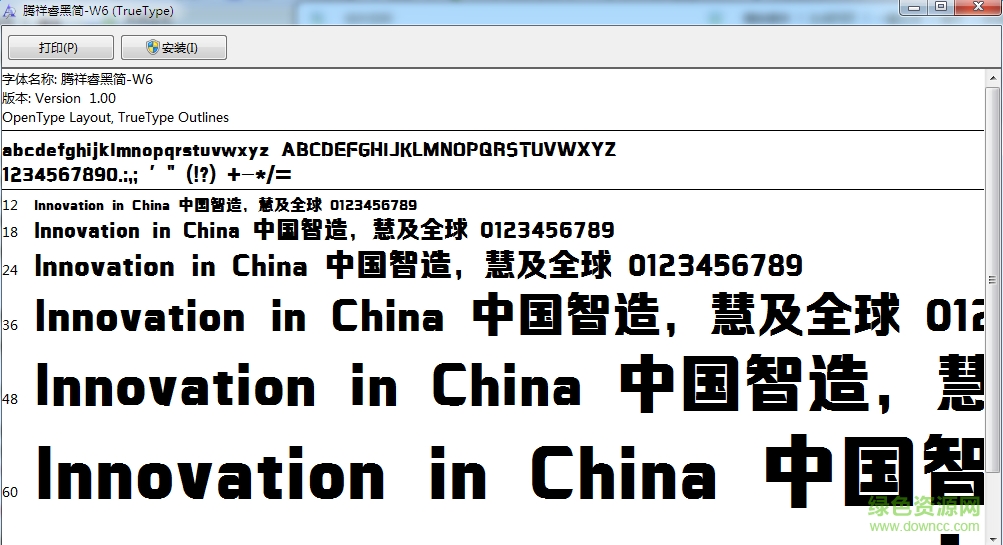
騰祥睿黑簡W6字體是一款粗壯、醒目的電腦黑體字體,與傳統(tǒng)黑體不同的是,這款字體既有傳統(tǒng)黑體方正、端莊筆形規(guī)范、實(shí)用的效果又賦予一定的美術(shù)裝飾特色,喜歡的朋友可以來綠色資源網(wǎng)下載!
騰祥睿黑簡-W6屬與黑體系列。睿黑系列賦予了黑體全新的設(shè)計(jì)理念。字形結(jié)構(gòu)方正、端莊,筆畫粗壯醒目、黑白均勻、行文貫通。塔形頓點(diǎn)、撇點(diǎn)和部分折筆處外圓角的設(shè)計(jì),使得字形看上去內(nèi)斂、圓潤、弱化了黑體尖銳和張揚(yáng)的感覺。